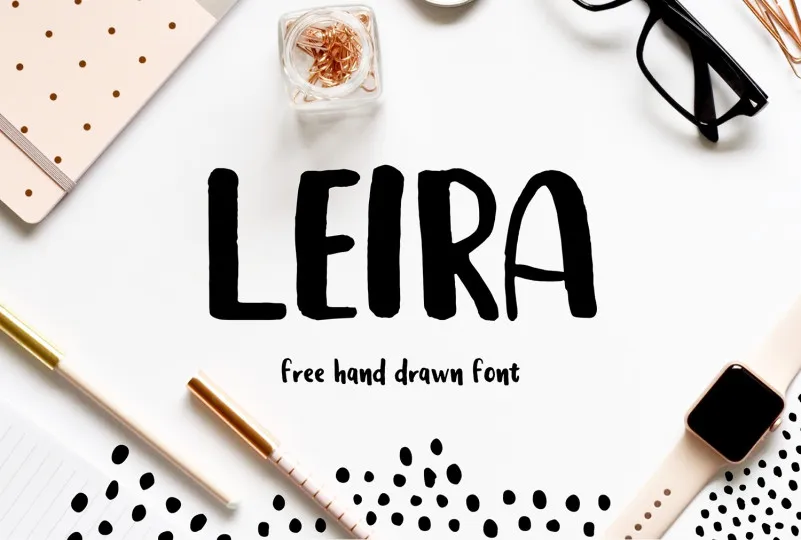
Leira Brush Font
Descubra uma nova maneira de expressar sua identidade visual com a Leira Brush Font. Esta elegante fonte feita à mão é perfeita para projetos que buscam um toque delicado e pessoal, como logotipos com estilos artesanais, cartões de convite, frases inspiradoras e designs diversos. Ideal tanto para identidades profissionais quanto para elementos visuais criativos, a Leira Brush Font oferece uma experiência única. Seus caracteres grandes chamam atenção e são fáceis de ler, enquanto os títulos manuscritos ganham um toque diferenciado que reforça o conceito da sua marca ou projeto. Os designers da fonte, Gatis Vilaks, capturaram perfeitamente a essência do desenho à mão em uma forma robusta e versátil, ideal para criar elementos visuais com atitude. Seja para logotipos criativos, cartazes de design, cartões personalizados ou embalagens de produto, a Leira Brush Font proporcionará um resultado visual único e envolvente. Feita especialmente para os amantes do estilo manuscrito e dos designs artesanais, esta fonte vem em uma versão com letras maiúsculas sólidas. E não se preocupe, todos os caracteres são incluídos: desde as letras minúsculas até números e símbolos. Essa fonte não só aprimora suas produções digitais, mas também adicionará um toque diferenciado ao seu projeto em impressão. Se você está buscando uma nova maneira de dar vida à sua ideia criativa ou quer adicionar algum charme artesanal aos seus designs digitais e físicos, não hesite em experimentar a Leira Brush Font. Ela certamente fará parte do seu leque de fontes favoritas no futuro.